硬笔书法是书法艺术百花园中的一颗璀璨耀眼的明珠,轻描淡写散发汉字书写的技巧。硬笔书法里有代表性的就是钢笔书法了,钢笔书法与广为人知的毛笔书法不同在于视觉呈现出的效果,毛笔的笔画较于粗壮而钢笔书法较于纤细字体识别度高。在毛笔书法基础上做加减法,有如去其肉筋存其骨质之意,艺术性与实用性并存。
行楷也被称作是“汉字行楷手写体字形”,是偏重于楷书书写的笔法,比楷书行笔自由,有笔行草规整的行书字体,在楷书的基础上简约书写笔画增强书写映带。这款“三极楚凡行楷”结构张弛有度,体现出从容淡定的气质,让人意犹未尽、百看不厌。适用于书刊、广告、包装、影视以及社交网络的个性化用字等。
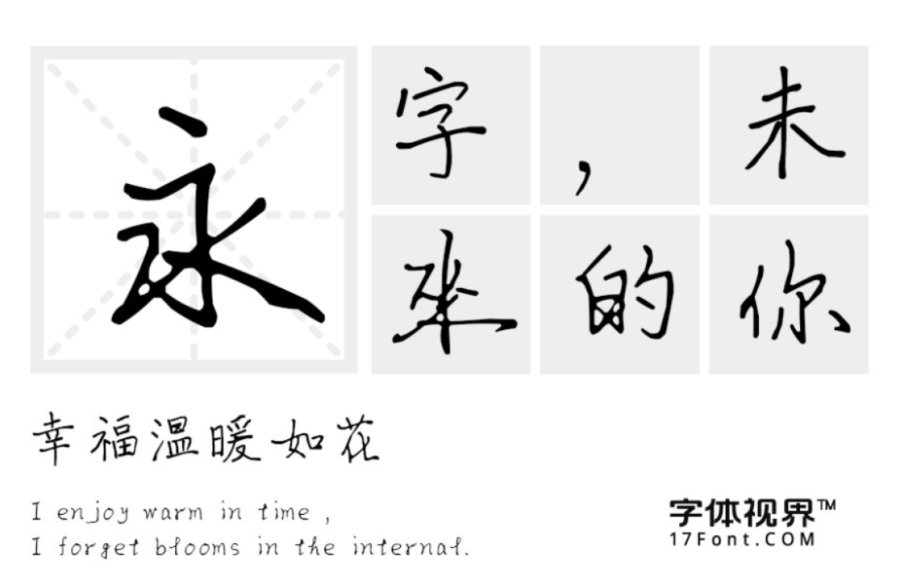
这款字体和刚刚上面介绍的那款字体也是同一种类型也是行楷。这款“三极崇德行楷”字体错落有致,笔画遒劲、刚柔并济。通过线条与结构的变化表现出书写着对书法艺术的认知感受。笔形上在楷书基础上的简化,打破过于平稳而产生静中求动的视觉态势。适用于正文或标题、文艺书刊、广告、包装设计以及社交网络的个性化用字等领域。
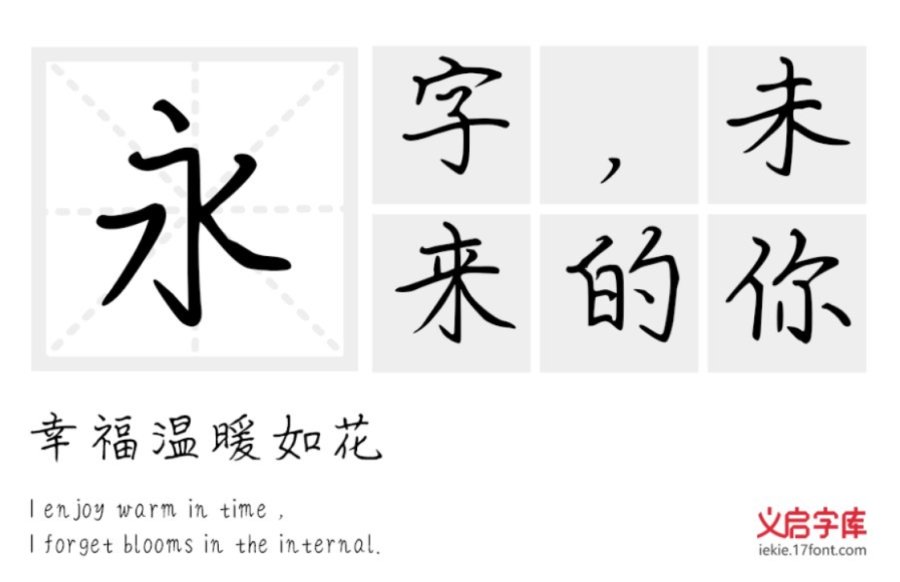
行书是比楷书更为快捷的书体,是现代日常书体。这款“义启刘圻硬笔行书”一款艺术与现代感相得益彰的结合体。此行书字体是由中国书法家协会会长,国际书画研究会终身会员兼全国书法大赛评委刘圻老师亲笔所写,笔法精湛干练,随性又不失功力,字如其人,见字如面。适用于书籍、ppt正文及标题、logo设计、广告设计、屏幕显示等领域。
钢笔书法的特色就是能做到易写易认,结构布局合理浑然天成,适用于多种设计应用领域,以上三款钢笔书法字体均可搜字体在字体视界的官网进行更深入信息的了解。